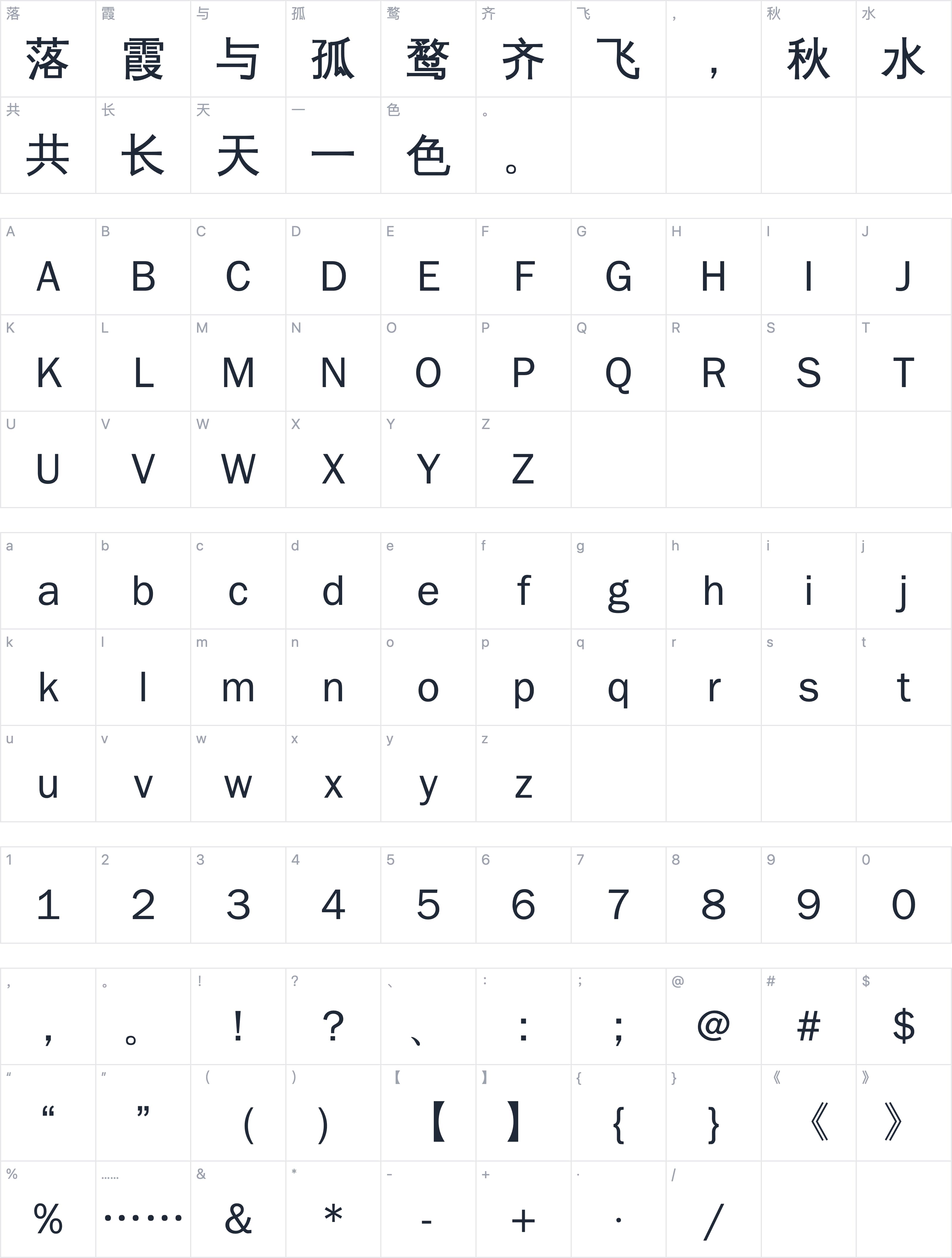
这款字体来自「文泉驿」,该字体包含了所有常用简体中文、繁体中文所需要的汉字(最新版本包含超过 27842 个汉字,完整覆盖 GB2312/Big5/GBK以及GB18030 标准字符集)。该字体同时还包含了日文、韩文和其他几十种语言符号。除此以外,该字体还嵌入了最新版本的文泉驿点阵宋体的中英文点阵,使得屏幕汉字显示清晰锐利,易于阅读。该字体为开源字体,可用于商业用途,无需获得许可。